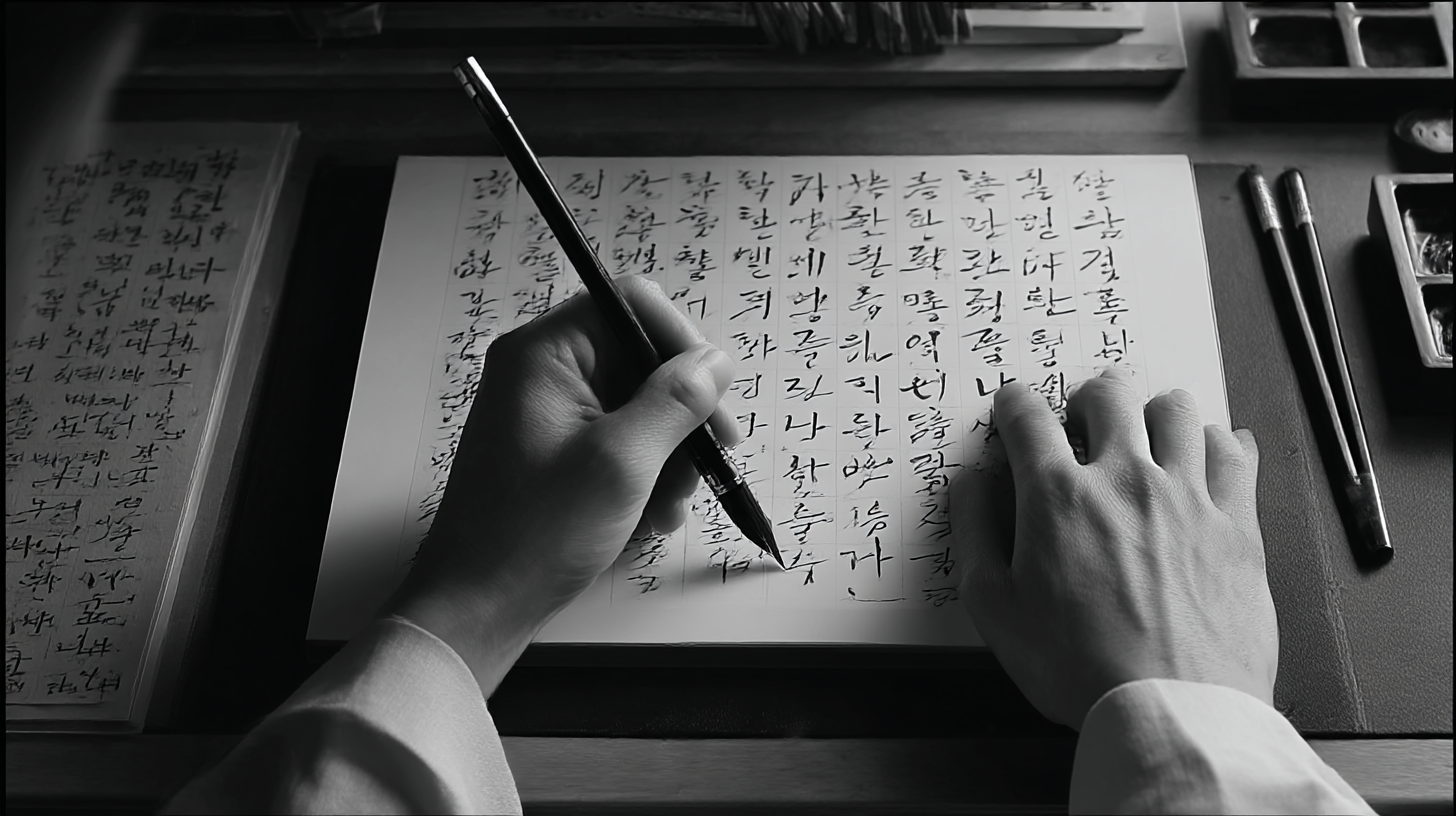
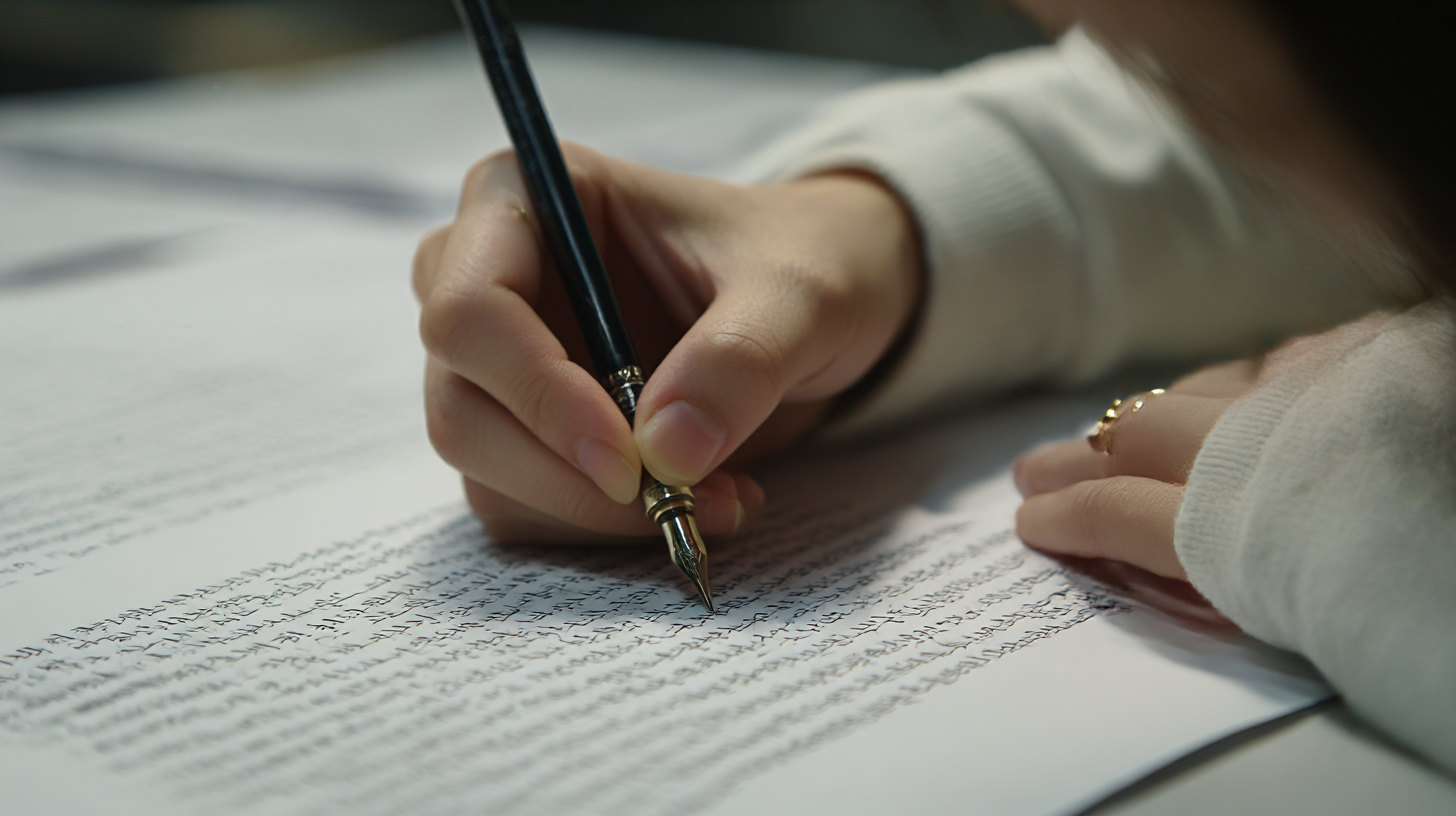
악필이 심한 사람을 위한 기초 글씨 교정법 많은 사람들이 자신의 글씨체에 만족하지 못하고 고민하곤 해요. ✍ 하지만 걱정하지 마세요! 꾸준한 연습과 올바른 방법만 있다면 누구나 예쁜 글씨를 쓸 수 있어요.
특히, 악필이 심한 사람들은 글씨 교정을 어디서부터 시작해야 할지 막막할 수 있어요. 그렇다면 기초부터 차근차근 배워보는 게 중요하겠죠? 이번 글에서는 악필의 원인과 문제점, 그리고 효과적인 교정법을 단계별로 알려드릴게요! 😊
손글씨는 단순한 글자가 아니라, 자신을 표현하는 중요한 도구예요. 글씨를 교정하면 필기 속도도 빨라지고, 가독성이 높아져 시험이나 업무에서도 훨씬 도움이 된답니다! 🎯
🧐 악필이 생기는 이유
악필은 타고나는 게 아니라, 잘못된 습관과 환경에서 비롯되는 경우가 많아요. 원인을 제대로 파악하면 교정하기도 훨씬 쉬워지겠죠?
1. 바르지 않은 필기 습관
어릴 때부터 바른 필기 자세를 익히지 않으면 글씨가 흐트러지기 쉬워요. 예를 들어, 연필을 너무 세게 잡거나 손목을 구부리고 쓰는 경우가 많아요.2. 손 근력 부족
손가락 힘이 부족하면 필기할 때 안정감이 떨어져 글씨가 흔들리거나 비뚤어질 수 있어요. 꾸준한 손 근력 운동이 필요해요.📊 악필 원인 비교
원인 영향 해결 방법 잘못된 필기 자세 글씨가 비뚤어지고 불균형해짐 바른 자세와 그립법 교정 손 근력 부족 글씨가 떨리고 균형이 맞지 않음 손 근력 운동 병행 너무 빠르게 쓰는 습관 획이 끊기고 난잡한 글씨가 됨 천천히, 정확하게 쓰는 연습 내가 생각했을 때, 악필을 고치기 위해 가장 중요한 것은 잘못된 습관을 바로잡는 것이에요. 아무리 연습해도 나쁜 습관이 남아 있으면 교정이 어렵거든요! 😃
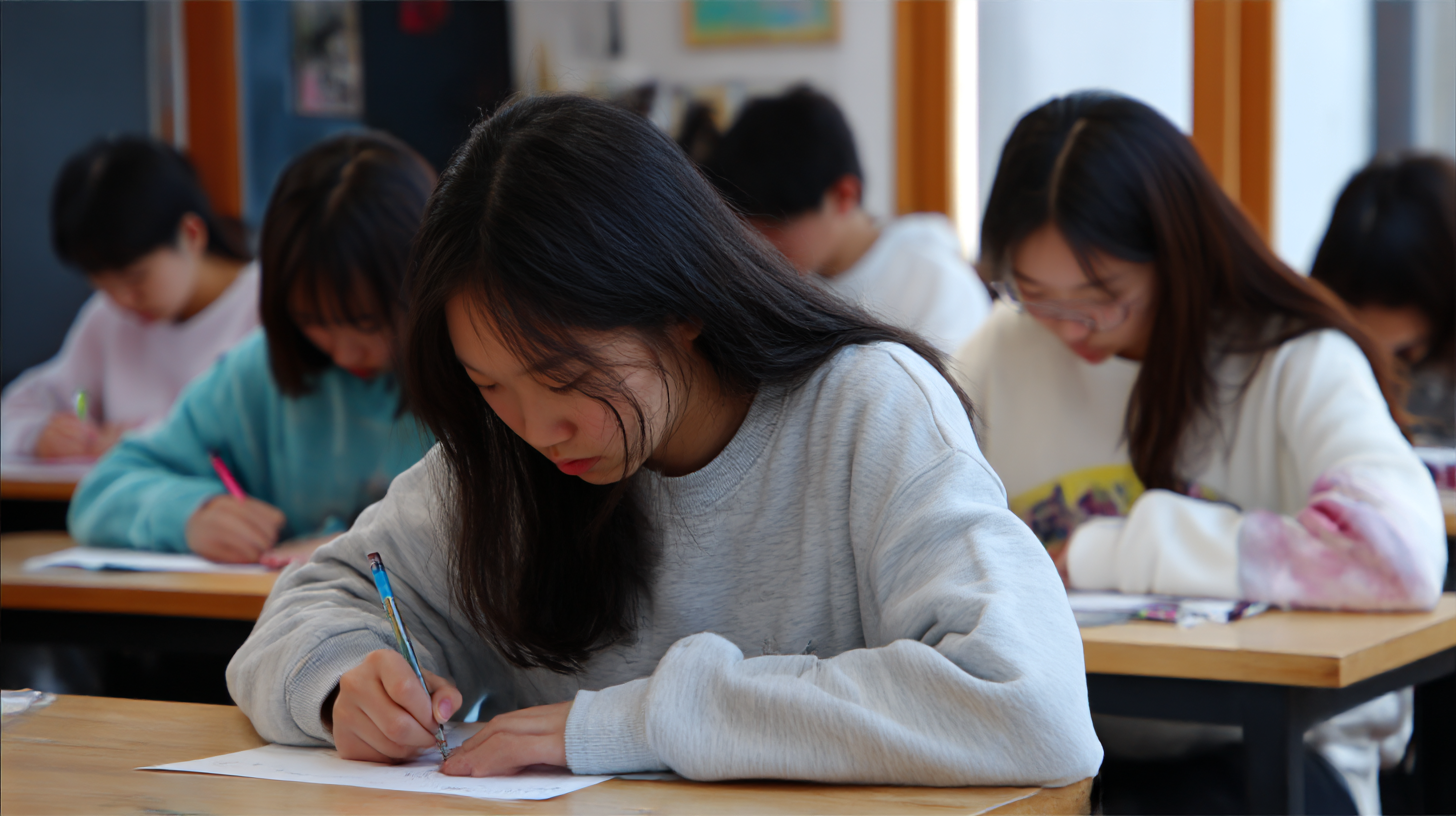
악필이 생기는 이유 ⚠ 악필이 가져오는 문제점
악필이 단순히 보기 안 좋은 문제만은 아니에요. 실제로 생활 속에서 여러 가지 불편함을 초래할 수 있답니다. 악필이 어떤 문제를 유발하는지 살펴볼까요?
1. 시험 필기 속도 저하
악필이 심하면 필기 속도가 느려지고, 시험에서도 불리해요. 글씨가 삐뚤빼뚤하면 빠르게 쓰기 어려워지고, 채점자가 글씨를 알아보기 힘들어 감점의 원인이 될 수도 있어요.2. 가독성 문제
본인이 쓴 글씨조차 나중에 읽기 힘든 경우가 있어요. 중요한 내용을 필기했더라도 해석이 어렵다면 다시 정리해야 하는 번거로움이 생기죠.3. 첫인상에 영향
글씨체는 사람의 성격을 반영한다고 알려져 있어요. 악필이 심하면 상대방에게 부주의하거나 성급한 인상을 줄 수 있어요. 특히 손글씨를 활용하는 직업에서는 더욱 중요한 요소가 될 수 있어요.📊 악필이 초래하는 주요 문제
문제 영향 해결 방법 시험에서 불리함 속도가 느려지고 가독성이 떨어짐 꾸준한 필기 연습으로 교정 자신의 글씨를 못 읽음 필기한 내용을 다시 정리해야 함 명확한 획과 간결한 글씨체 연습 첫인상에 부정적 영향 부주의한 사람처럼 보일 수 있음 일정한 글씨체로 정리된 필기 연습 내가 생각했을 때, 악필은 단순히 "보기 안 좋은 글씨"의 문제가 아니라 실생활에서 불편함을 초래하는 요소예요. 하지만 꾸준한 연습을 통해 얼마든지 개선할 수 있답니다! ✨
그렇다면 악필을 교정하려면 어떤 방법을 활용해야 할까요? 기초적인 글씨 교정법을 3단계로 정리해서 알려드릴게요! ✍
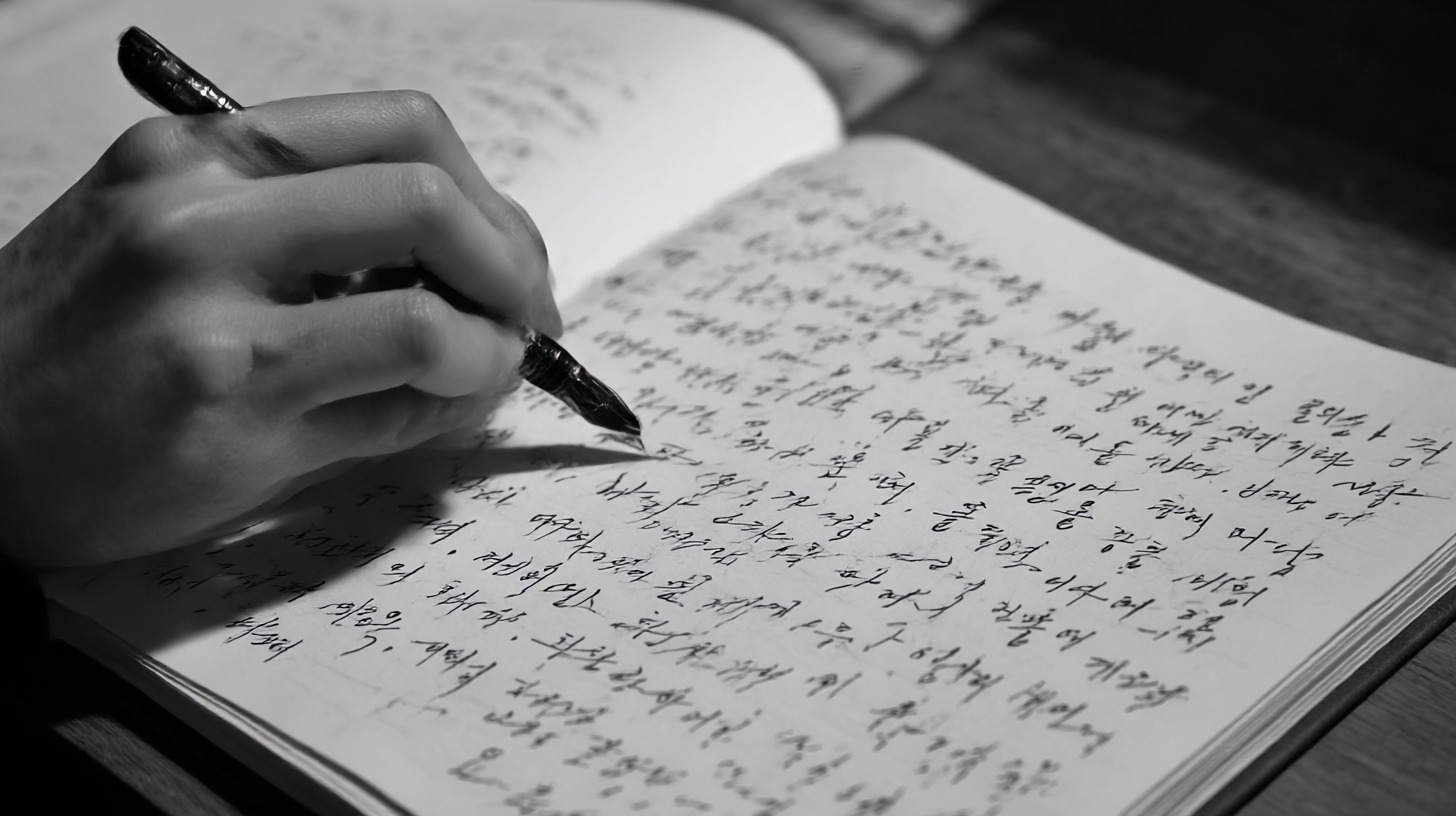
악필이 가져오는 문제점 📖 기초 글씨 교정법 3단계
악필 교정은 하루아침에 이루어지지 않아요. 하지만 올바른 방법으로 꾸준히 연습하면 누구나 깔끔한 글씨체를 가질 수 있어요! ✍
1단계: 필기 자세와 그립법 점검
바른 글씨체를 가지려면 올바른 필기 자세와 펜 잡는 법부터 시작해야 해요. 잘못된 자세로 글씨를 쓰면 아무리 연습해도 개선이 어렵답니다.✅ 올바른 필기 자세:
- 허리를 곧게 펴고 편안한 자세 유지하기
- 팔꿈치를 책상에 가볍게 올려 안정적으로 필기하기
- 손목을 너무 구부리지 않고 자연스럽게 움직이기✅ 올바른 펜 잡는 법:
- 엄지, 검지, 중지로 가볍게 잡기
- 손가락 힘을 너무 주지 않기
- 손목과 팔 전체를 이용해 필기하기📌 필기 자세 & 그립법 비교
항목 올바른 방법 잘못된 방법 필기 자세 허리를 곧게 펴고 편안한 자세 유지 고개를 숙이고 구부정한 자세 펜 잡는 법 손가락 세 개로 가볍게 잡기 펜을 너무 꽉 쥐거나 한 손가락만 사용 손목 사용 팔 전체를 이용해 자연스럽게 움직이기 손목만 움직이고 힘을 많이 줌 2단계: 획의 균형 연습
글씨가 삐뚤어지거나 비대칭이 심하다면, 획의 균형을 맞추는 연습이 필요해요. 먼저 가로선과 세로선을 일정한 간격으로 긋는 연습부터 해보세요.✏ 연습 방법:
- 직선, 곡선을 일정한 간격으로 긋기
- 한 글자씩 천천히 쓰면서 균형 맞추기
- 연습장이나 교정 노트 활용하기3단계: 글씨 크기와 간격 맞추기
글씨 크기가 일정하지 않거나 글자 간격이 들쭉날쭉하면 가독성이 떨어져요. 적절한 크기와 간격을 유지하는 연습이 필요해요.✏ 연습 방법:
- 네모 칸이 있는 노트나 점선 노트 활용
- 일정한 크기로 반복해서 글자 쓰기
- 문장을 적을 때 글자 간격을 의식하며 연습하기내가 생각했을 때, 이 3단계를 차근차근 따라 하면 악필이 자연스럽게 개선될 거예요! 😊
이제 실제로 효과적인 손글씨 연습법을 알아볼까요? 🚀
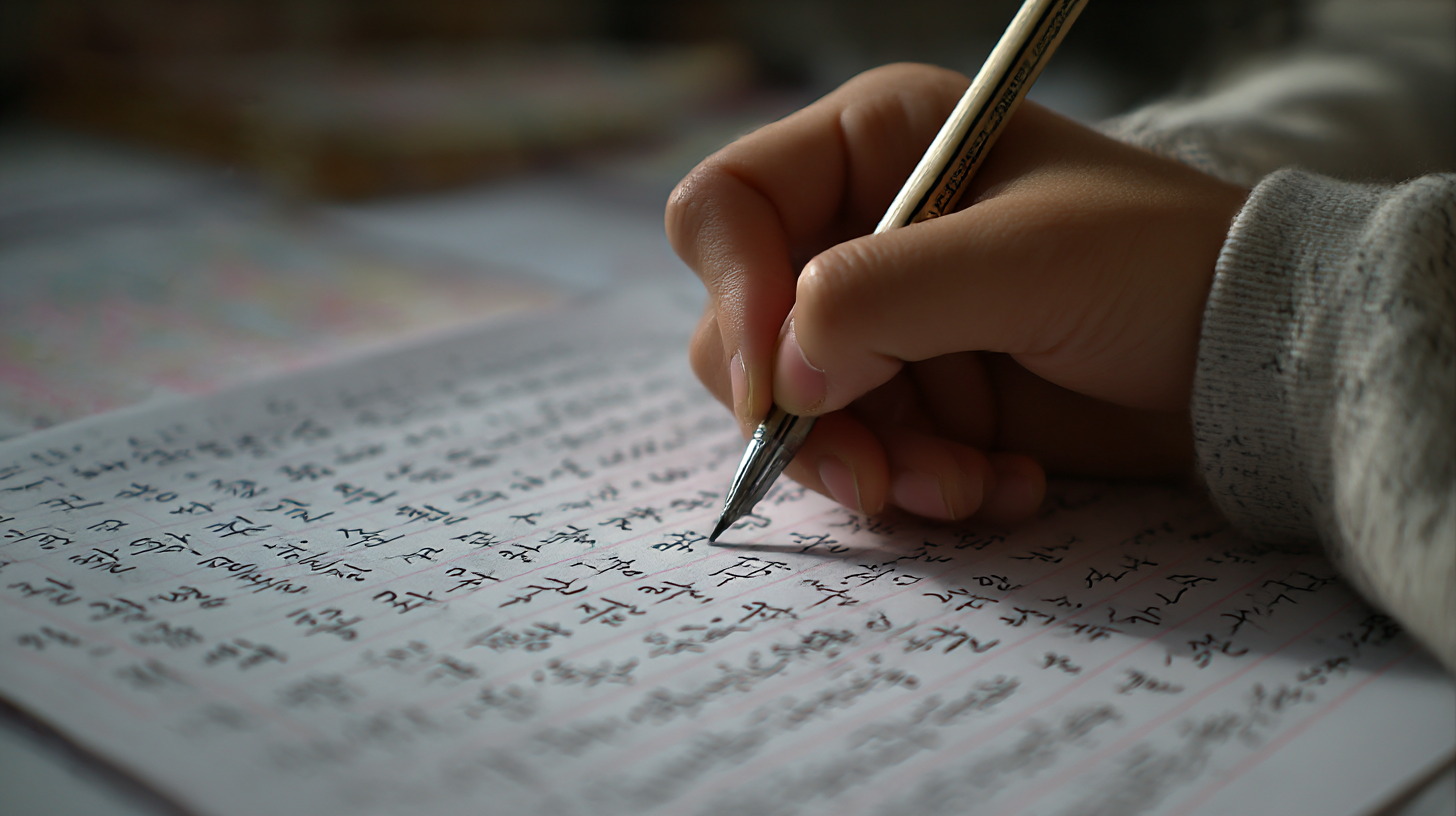
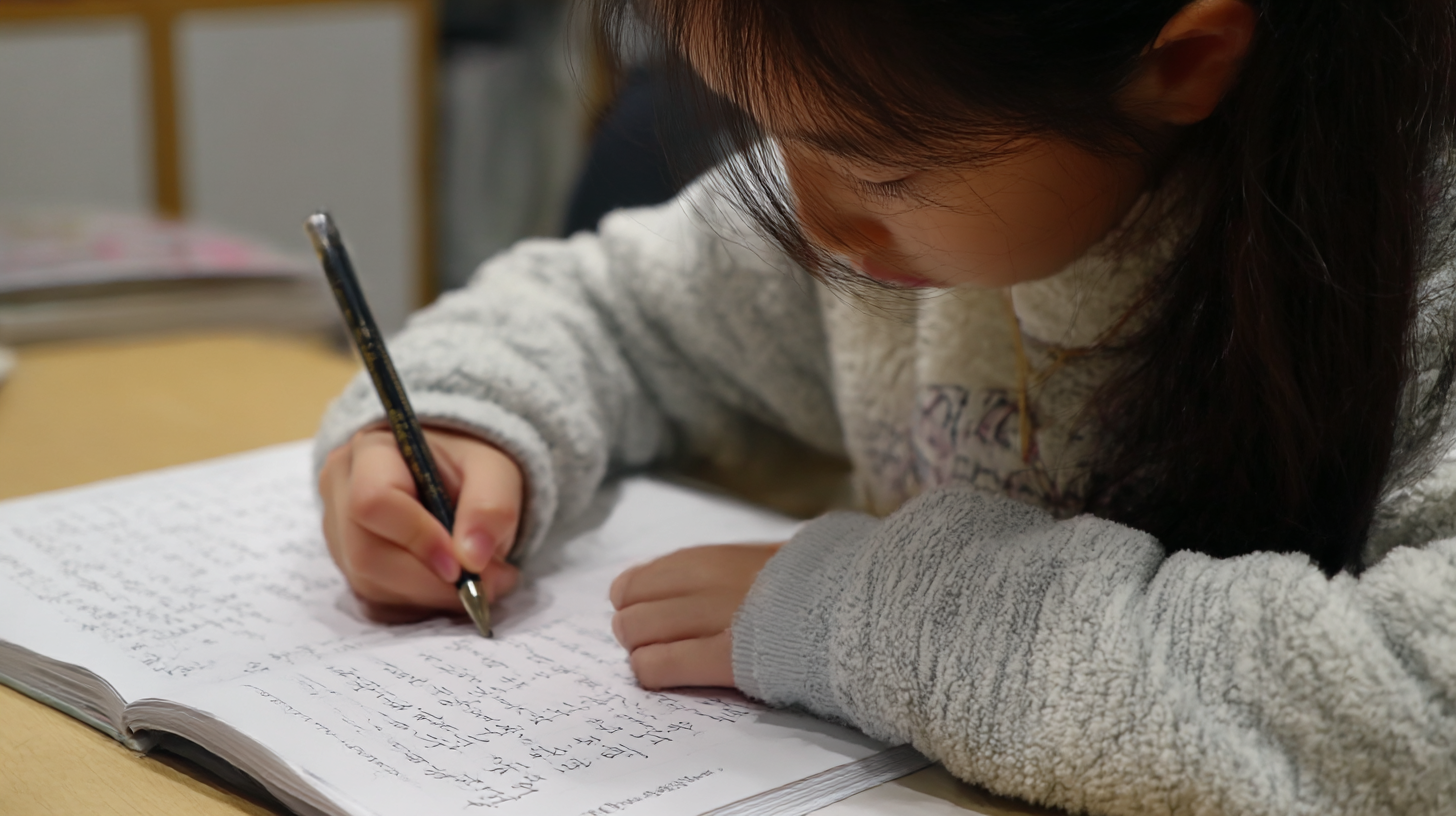
기초 글씨 교정법 3단계 📝 효과적인 손글씨 연습법
손글씨 교정을 할 때 가장 중요한 것은 꾸준한 연습이에요. 하지만 무작정 글씨를 반복해서 쓴다고 해서 반드시 좋은 글씨체가 되는 것은 아니랍니다. ✍
악필을 효과적으로 교정하려면 체계적인 연습법이 필요해요. 오늘 소개할 방법을 활용하면 보다 빠르게 원하는 글씨체를 만들 수 있을 거예요! 😊
1. 기초 획 연습
글씨체를 바꾸려면 먼저 기본 획을 정확하게 쓰는 연습부터 해야 해요. 직선, 곡선, 점 등을 정확하게 쓰는 것이 중요한데, 기본 획 연습이 되어야 글자가 균형 있게 나와요.✅ 연습 방법:
- 가로선, 세로선, 대각선 긋기 연습
- 일정한 간격으로 원과 삼각형 그리기
- 점선을 따라 직선 긋기📊 기초 획 연습 비교
연습 방법 효과 추천 도구 직선 긋기 획을 균일하게 유지하는 연습 도트 연습장, 일반 노트 곡선 연습 부드러운 필기감 습득 스케치북, 교정 노트 점선 따라 쓰기 획의 균형과 정렬 연습 초등용 글씨 교정 노트 2. 하루 10분 따라쓰기 연습
책이나 명언을 따라서 쓰는 것도 좋은 연습 방법이에요. 눈으로 보고 따라 쓰면서 자연스럽게 글씨체를 교정할 수 있죠.✅ 추천 연습 방법:
- 좋아하는 문장을 골라 하루 10번씩 쓰기
- 글씨 크기를 일정하게 유지하기
- 한 글자씩 천천히 쓰면서 필기 습관 교정하기3. 글자 간격과 정렬 맞추기
예쁜 글씨체는 단순히 글씨 모양뿐만 아니라 일정한 간격과 정렬도 중요해요. 글자 간격을 신경 써서 연습하면 훨씬 정돈된 글씨를 쓸 수 있어요.✅ 연습 방법:
- 연습장에 가이드라인을 그리고 따라쓰기
- 일정한 글자 크기를 유지하면서 필기
- 세로 정렬이 맞는지 확인하면서 쓰기내가 생각했을 때, 손글씨 연습은 단순 반복보다는 체계적인 연습법이 훨씬 효과적이에요! 😊
이제 바른 글씨체를 만들기 위해 필기 자세까지 점검해볼까요? ✍
효과적인 손글씨 연습법 🧑🎓 바른 글씨체를 위한 필기 자세
아무리 글씨를 예쁘게 쓰려고 해도 필기 자세가 올바르지 않으면 교정이 어렵고 손도 쉽게 피로해져요. 필기 속도와 가독성을 높이려면 바른 자세부터 익히는 것이 중요해요! 😊
1. 올바른 필기 자세
필기할 때 허리를 곧게 펴고, 고개를 너무 숙이지 않는 것이 중요해요. 책상과 몸 사이의 거리를 적절히 유지해야 장시간 필기해도 피로감이 적어요.✅ 필기 자세 체크리스트
- 허리는 곧게 펴고 어깨에 힘을 빼기
- 팔꿈치를 책상에 가볍게 올려 안정적인 필기
- 고개를 너무 숙이지 않고 시선은 노트와 일정 거리 유지📌 바른 필기 자세 vs 잘못된 필기 자세
항목 바른 자세 잘못된 자세 허리 곧게 펴고 편안한 상태 유지 구부정하게 숙이고 필기 손 위치 손목과 팔을 함께 움직이며 필기 손목만 사용하여 힘이 많이 듦 시선 노트와 적절한 거리 유지 노트에 얼굴을 바짝 붙임 2. 손과 손목의 자연스러운 움직임
글씨를 쓸 때 손가락만 사용하면 필기가 힘들어지고 속도도 느려져요. 팔과 손목을 함께 사용해야 부드럽게 필기할 수 있어요.✅ 손과 손목 사용법
- 손목을 고정하지 않고 팔과 함께 움직이기
- 펜을 너무 꽉 쥐지 않고 자연스럽게 잡기
- 손목이 지나치게 꺾이지 않도록 주의3. 편안한 필기 환경 만들기
필기 환경도 글씨체에 영향을 줘요. 너무 낮거나 높은 책상, 어두운 조명은 필기 습관을 망칠 수 있어요.✅ 필기 환경 점검하기
- 적절한 높이의 책상과 의자 사용
- 조명은 밝고 자연광에 가깝게 유지
- 손목이 편안한 각도로 유지되는지 확인내가 생각했을 때, 바른 필기 자세만 제대로 익혀도 글씨체가 훨씬 좋아질 거예요! 😊
이제 초보자도 쉽게 사용할 수 있는 글씨 교정 필수템을 추천해드릴게요! 🖊
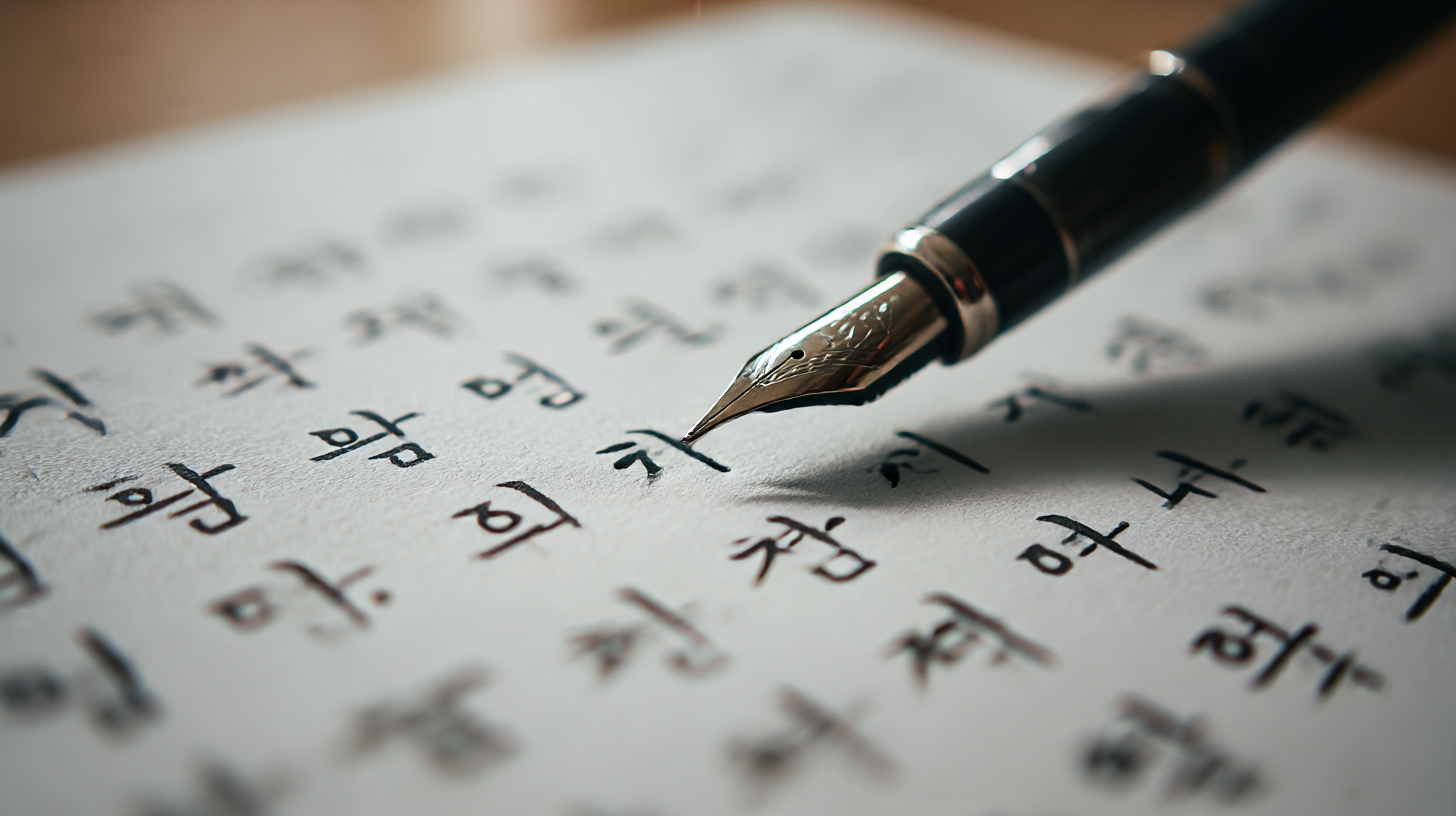
바른 글씨체를 위한 필기 자세 🖊 초보자를 위한 글씨 교정 필수템
글씨 교정을 할 때 도구를 잘 활용하면 훨씬 더 빠르고 효과적으로 연습할 수 있어요. 📝 특히 초보자는 획 교정이 쉬운 펜과 연습장을 선택하는 것이 중요해요!
오늘 소개할 필수템 5가지를 활용하면 보다 편하게 글씨 연습을 할 수 있을 거예요! ✨
1. 글씨 교정 노트
획을 일정하게 유지하고 글자 크기를 맞추는 데 도움을 줘요. 처음에는 점선 가이드가 있는 연습장이 좋아요.2. 필기감 좋은 펜
손에 부담을 줄이고 필기 속도를 높이려면 부드러운 필기감의 펜을 사용하는 것이 좋아요.3. 글씨 교정 클립
A7. 태블릿 필기 연습도 효과가 있어요. 하지만 종이에 쓰는 것과 감각이 다르므로, 가능하면 종이 필기와 병행하는 것이 가장 좋아요.
Q8. 글씨가 쉽게 삐뚤어지는데 해결 방법이 있을까요?
A8. 네! 네모 칸이 있는 노트나 점선이 있는 연습장을 활용하면 글씨를 일정하게 정렬하는 데 도움이 돼요. 또한, 한 글자씩 천천히 써보는 연습도 효과적이에요.
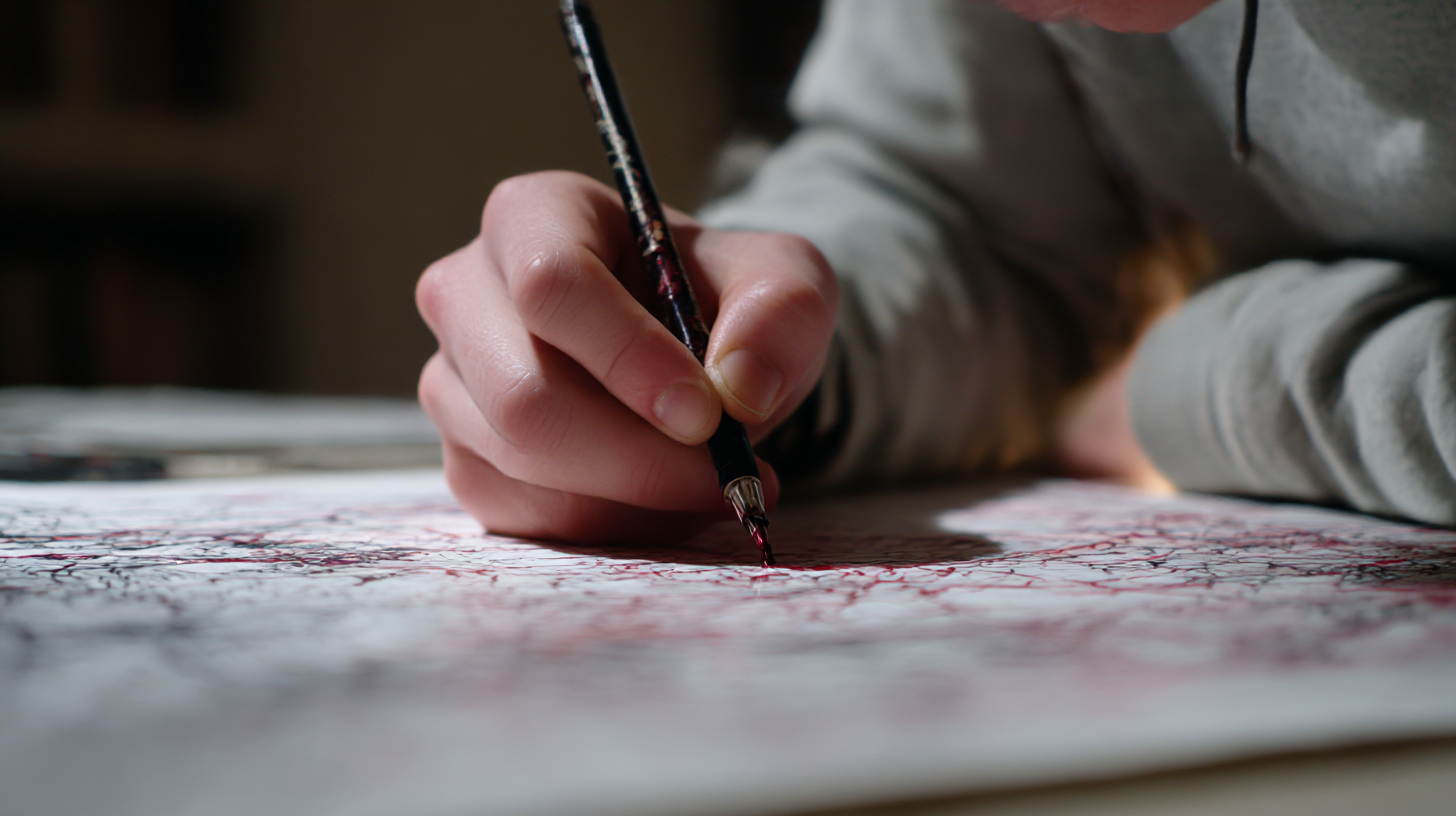
📌 마무리하며
지금까지 악필 교정을 위한 다양한 방법을 살펴봤어요! ✍
글씨 교정은 하루아침에 되는 것이 아니지만, 꾸준히 연습하면 반드시 개선될 수 있어요! 특히 바른 자세, 적절한 도구 활용, 체계적인 연습이 가장 중요하답니다. 😊
만약 필기 속도를 높이고 싶다면 타이머 연습법과 획 연습을 병행하는 것이 좋아요. 그리고 글씨를 깔끔하게 유지하고 싶다면 일정한 간격과 크기 맞추기를 연습하는 것이 필수예요!
오늘 배운 방법을 활용해서 더 예쁜 손글씨를 만들어 보세요! 여러분도 명필이 될 수 있어요! 🎯